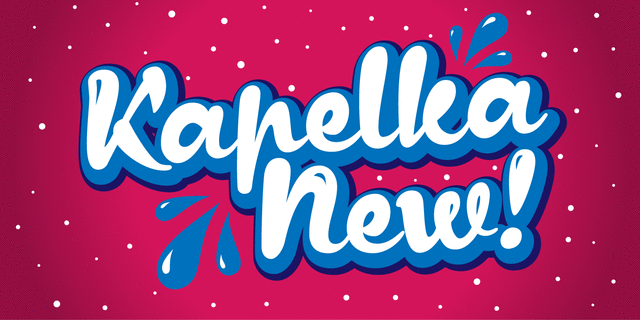
Капелька Новая — мягкий и дружелюбный акцидентный шрифт, в основе которого лежит принцип письма круглой кистью. Подходит для упаковки, заголовков в детских книгах и любых надписей неформального, домашнего характера. Шрифт разработан дизайнером Захаром Ящиным и выпущен компанией ПараТайп в 2015 году.
наивный, веселый, вкусный, жидкий, лихой, неустойчивый, подвижный, непоседливый, смешной, радостный, сладкий, шутливый, ягодный, фруктовый, шаловливый, балованный, динамичный, приветливый, детский, живой, милый, мультяшный, новогодний, домашний, летний, счастливый, проворный, свободный
мультфильм, анимация, десерт, варенье, конфеты, мармелад, кафе, детская книжка, кондитерская, сладости, мороженное, раскраска, хенд мейд, пицца, зоопарк, зоомагазин, животные, отдых, лагерь, булочная, цирк, новый год, базар, соус, кетчуп, фаст фуд, еда, жвачка, подгузник, чипсы, аквадискотека, графика, иллюстрация Стилистика: